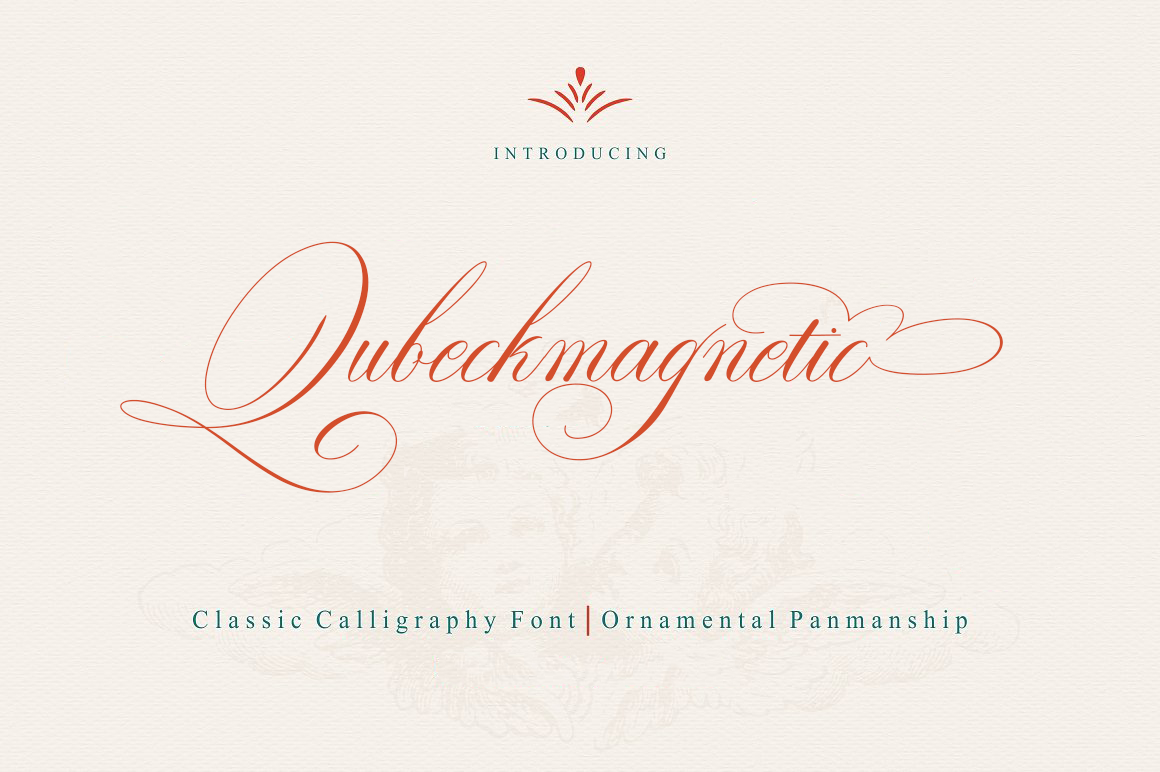
Qubeckmagnetic Script Font – Download Grátis
A Qubeckmagnetic é uma tipografia formal com estilo esguichado, que oferece àqueles interessados na estética do século médio italiano a sensação única dos pinceladas femininos. Com sua característica OpenType, ela transmite um sentimento vívido e autêntico da escrita a mão de mulheres italianas no período medievais. Ideal para design editorial e gráfico, esta fonte apresenta uma forma elegante e sofisticada que certamente se destacará em qualquer projeto que você estiver desenvolvendo. Seja para editoriais respeitosos ou designs visuais impactantes, a Qubeckmagnetic está aqui para oferecer aquela explosão de personalidade que seu design pode precisar.